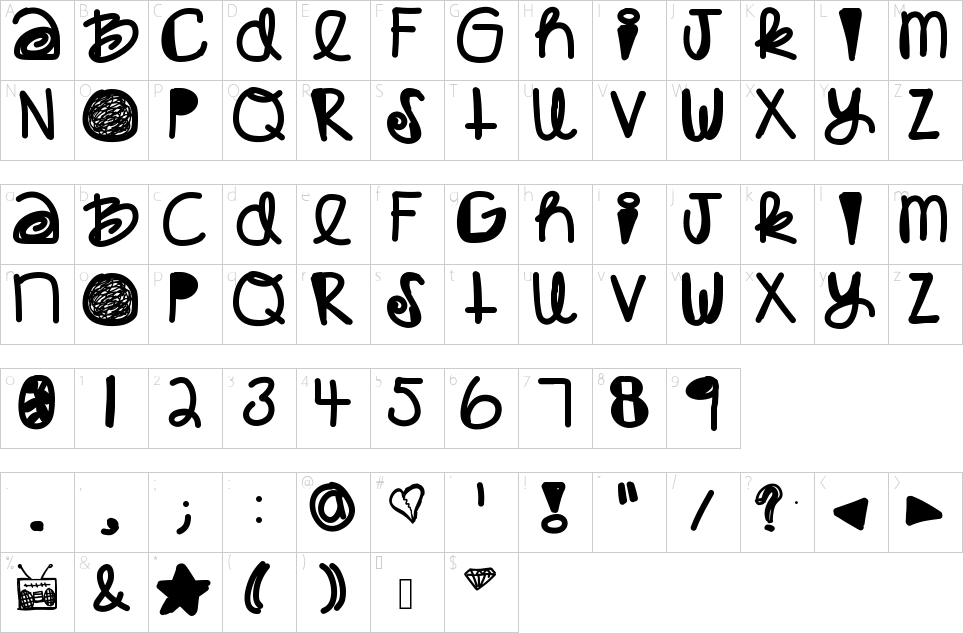
Babaganoosh Font – Download Grátis
A Babaganoosh é uma elegante e sofisticada fonte que se destaca na categoria das fontes grátis. Desenvolvida pelo designer desconhecido Des Gomez, esta hermosa font permite que você personalize qualquer documento ou projeto com estilo. Com um design minimalista mas de grande impacto visual, a Babaganoosh é ideal para textos legíveis e elegantes. Esta font foi baixada mais de 9.100 vezes, demonstrando sua popularidade e qualidade. Instale-a em seu próximo projeto e inspire-se com o charme desta fonte única.